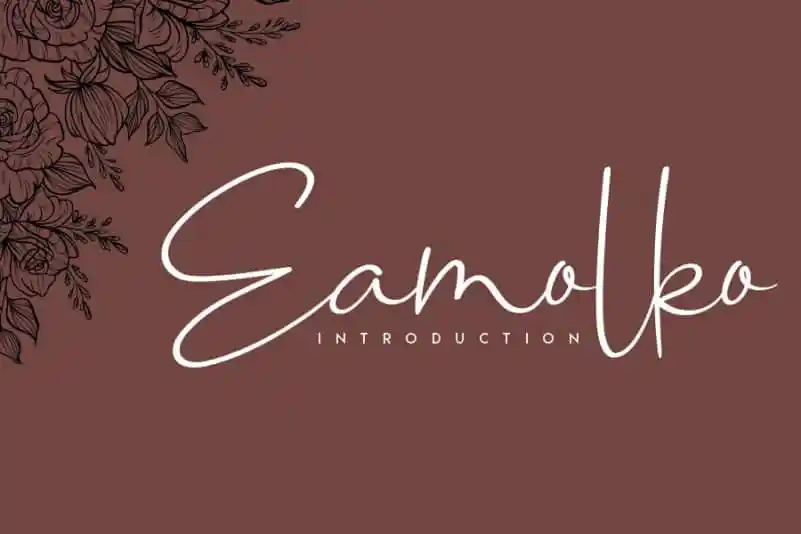
Eamolko Handwritten Font – Download Grátis
A Eamolko Handwritten Font é uma escolha inteligente para designers que buscam dar aos seus projetos um toque delicado e sofisticado. Isso se deve à sua natureza única, com traços fluidos que lembram a elegância do estilo de escrever de velhas mãos, mas em um formato digital perfeito para o mundo da moda moderna. Esta fonte é ideal tanto para uma reviravolta emocional no branding ou nas assinaturas das empresas, quanto para dar um toque romântico e autêntico a designs criados para ocasiões especiais como casamentos e eventos de aniversário. Ela vai muito bem em logotipos e rótulos, proporcionando o equilíbrio perfeito entre a elegância clássica e a sofisticação moderna. Sem dúvida, Eamolko Handwritten Font é uma fonte que pode ser usada com segurança para dar um tom pessoal e memorável a qualquer design projetado.